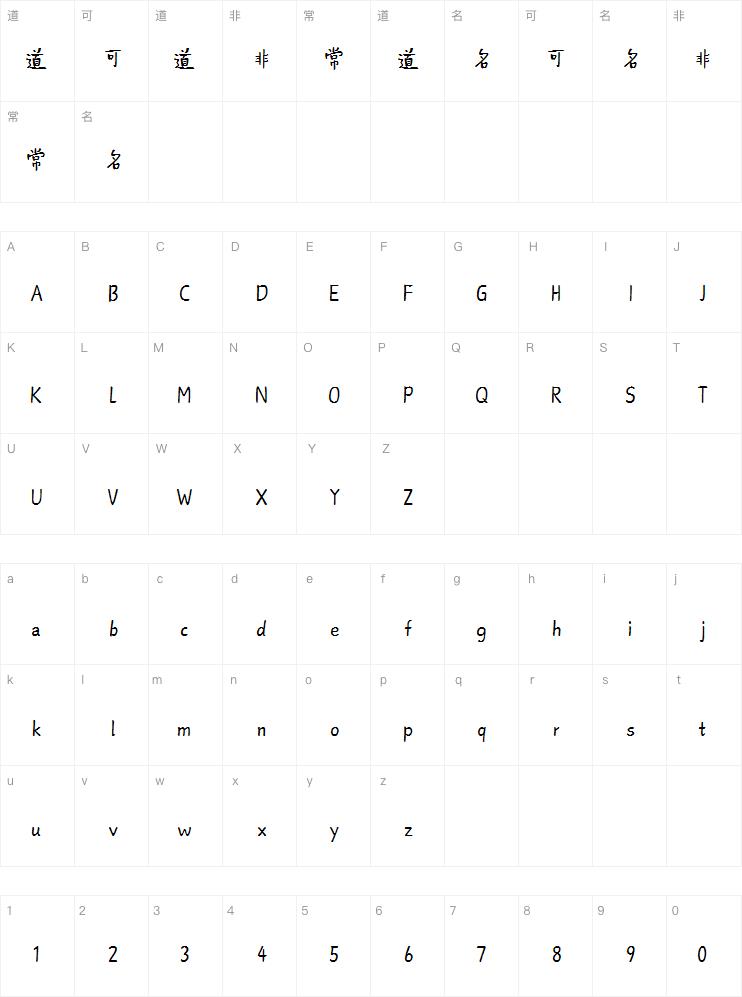
山海清夏日记,是一款全新的字体,包含汉字9169个,符号200+个。该字体是一款小清新手书字体,该字体字形灵动多变,清新淡雅,同时融入手写风笔势,各种连笔笔画,整体笔触圆润,活泼清新,造型生动有趣,具有灵活的适用性,天真俏皮又不失清新感。该字体字形随手写习惯大小不一,各个字的大小随字形的不同而呈现不同的大小,但是在变化中寻求平衡,在多变的同时有保持整体均衡匀称,使得整个字体更具有手写感的温度和节奏感,整体笔触圆润,灵动笔画贯穿笔画始终,内涵丰富,弧度柔和,撇笔平缓舒展,尽显清新灵动。这款字体清新淡雅而不失灵动,静中有动,收放有序,适合作为标题字体应用于书籍封面、影视标题、展览广告等多种场景。